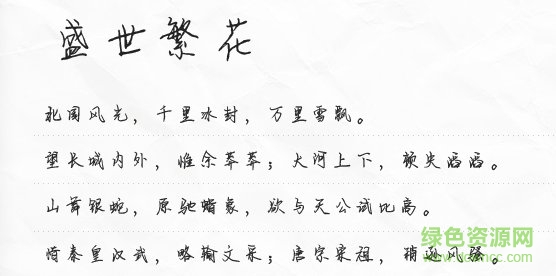
盛世繁花體字體
盛世繁花字體是一款獨具古風運維的藝術(shù)字體,字跡娟秀婉約,給你寧靜致遠的觀賞體驗,讓文字變得更有內(nèi)涵,喜歡的朋友就來綠色資源網(wǎng)下載收藏吧!
盛世繁花體字體特色
執(zhí)年華為筆,寫盡一生風月無邊;以江山為曲,歌盡一場盛世繁花。
本字體有文道字庫推出,以古風為魂,以手寫體為魄,為大家?guī)順O為舒適的視覺體驗,可廣泛運用于屏幕設(shè)計、詩歌編輯、海報印刷等場合。